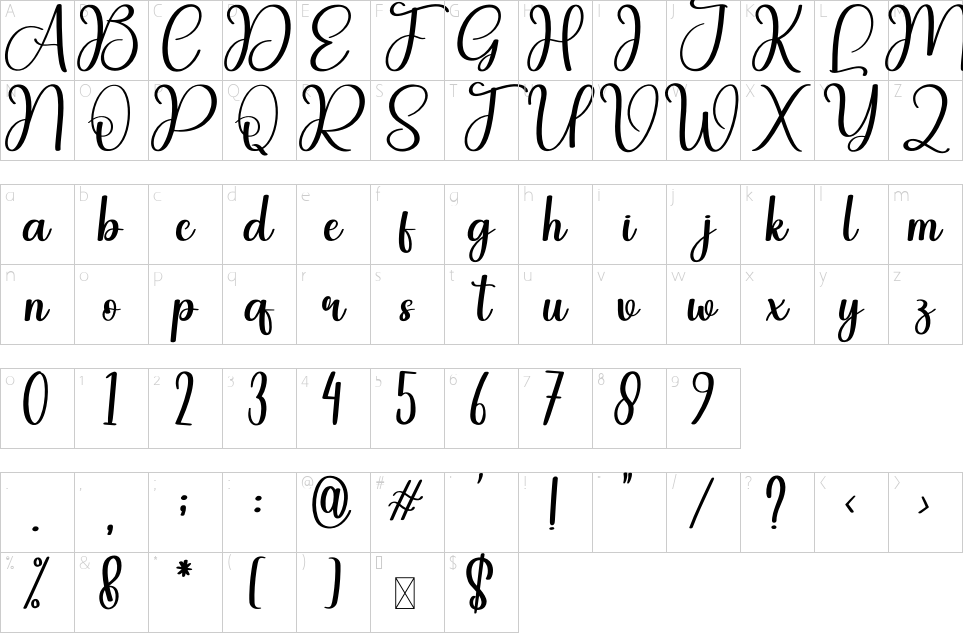
A Match Font é uma opção ótima para quem procura uma fonte moderna e versátil, disponível de graça para download tanto em Windows quanto Mac. Desenvolvida por William Jhordy, esta fonte foi projetada para complementar diversos estilos de design. Seus traços elegantes e arredondados permitem que seja usada em variadas aplicações, do design gráfico até o design editorial. Com seu design clean e minimalista, a Match Font se destaca por sua simplicidade e facilidade de uso, tornando-a uma escolha interessante para qualquer projeto que busque um look minimalista e clean. E, embora a fonte não seja originalmente produzida pela Match, é uma ótima opção para quem busca qualidade e estabilidade em suas fontes de graça. Compartilhe seu design com a Match Font e deixe sua marca em cada projeto.